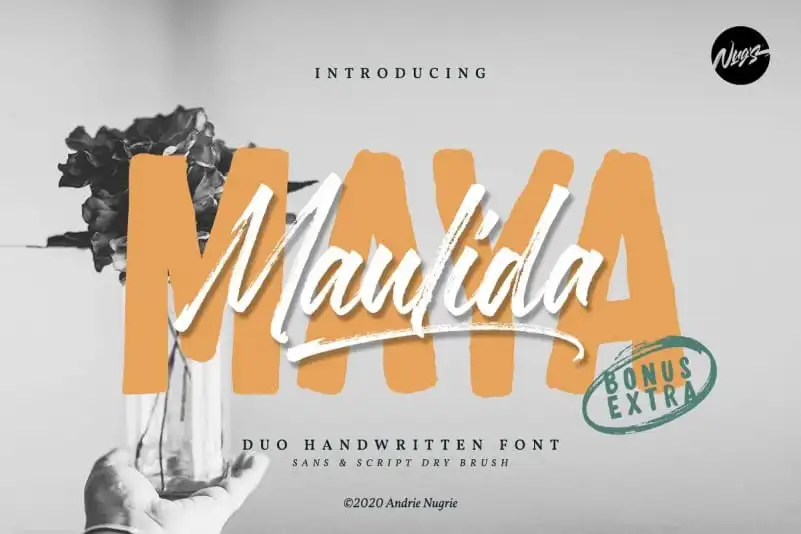
Maulida Maya Brush Font – Download Grátis
A Maulida Maya Brush Font é uma fonte criada pelo projeto Nug’s Project que oferece uma experiência visual única para os entusiastas do design gráfico. Este script brush font é perfeitamente adaptado para aplicativos variados como assinaturas, identidade de marca, wedding invitations, moda, fotografias, efeitos em fotos, títulos para anúncios, banners sociais, capas de livros, embalagens, citações escritas a mão, cartões de saudação e publicidade. Com seu conjunto completo de caracteres maiúsculas e minúsculas, caracteres gregos, números, alfabéticos alternativos, ligantes e suporte multilíngue, esta fonte atende todas as suas necessidades de design. Engane-se se pensar que a Maulida Maya Brush Font é apenas para aqueles que desejam um visual elegante. Ela também oferece um toque delicado e autêntico que tornará seu trabalho ainda mais pessoal e amigável.